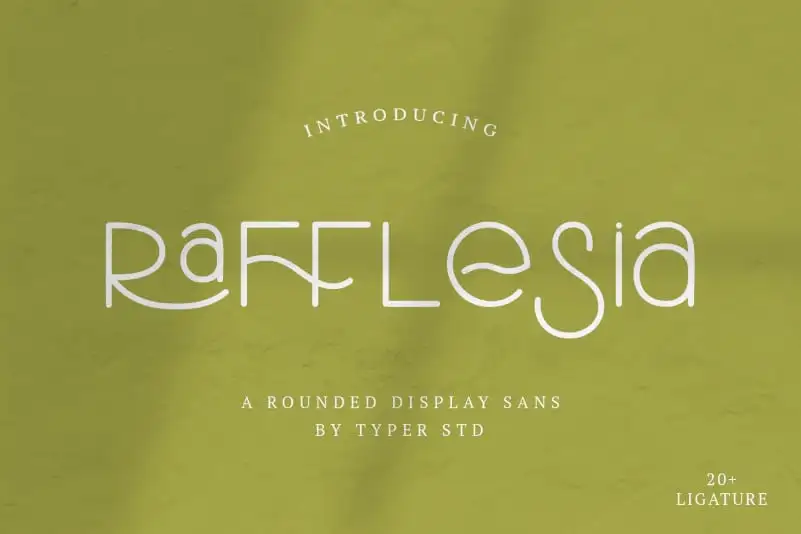
Rafflesia Display Font
A Rafflesia Display Font é uma elegante escolha para qualquer projeto que busque aprimorar a identidade visual com estilo moderno. Feita pelo famoso designer de fontes, Rinto Hardianto, essa fonte combina um acabamento redondo e sofisticado com detalhes divertidos de ligação, tornando-a perfeita tanto para elementos de marca como para aplicações em caixas de embalagem e logotipos. Suave e moderna ao mesmo tempo, a Rafflesia Display Font é ideal para eventos especiais ou qualquer outra aplicação que busque um toque divertido e único à sua identidade visual. Suas ligações coloridas e interativas tornam-a perfeita para manchas d’água, capas de livro, slogans, logos, embalagens, elementos de marca e até mesmo eventos especiais. Composta para diferentes usos, a Rafflesia Display Font é uma fonte indispensável para designers buscando um toque moderno em seus projetos.